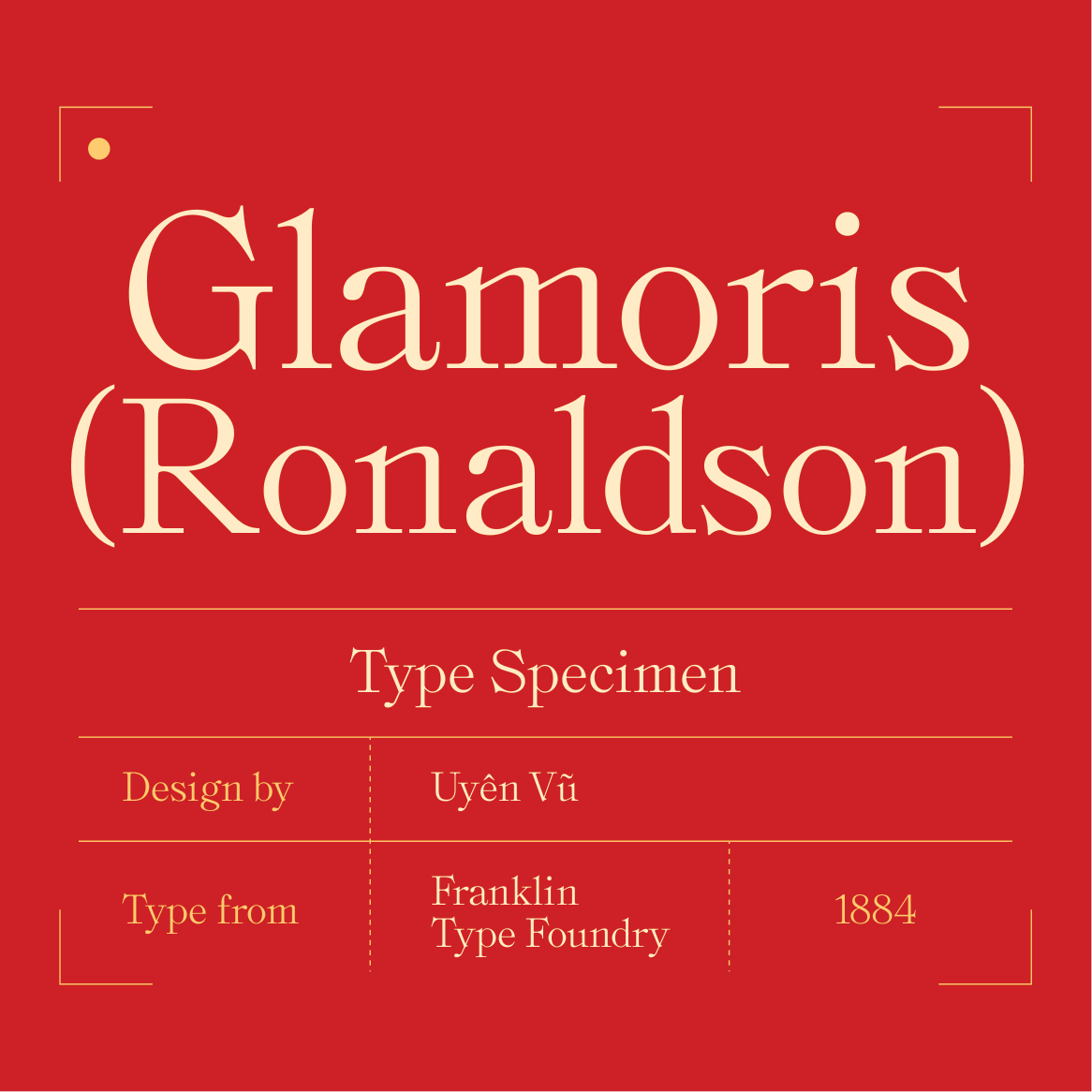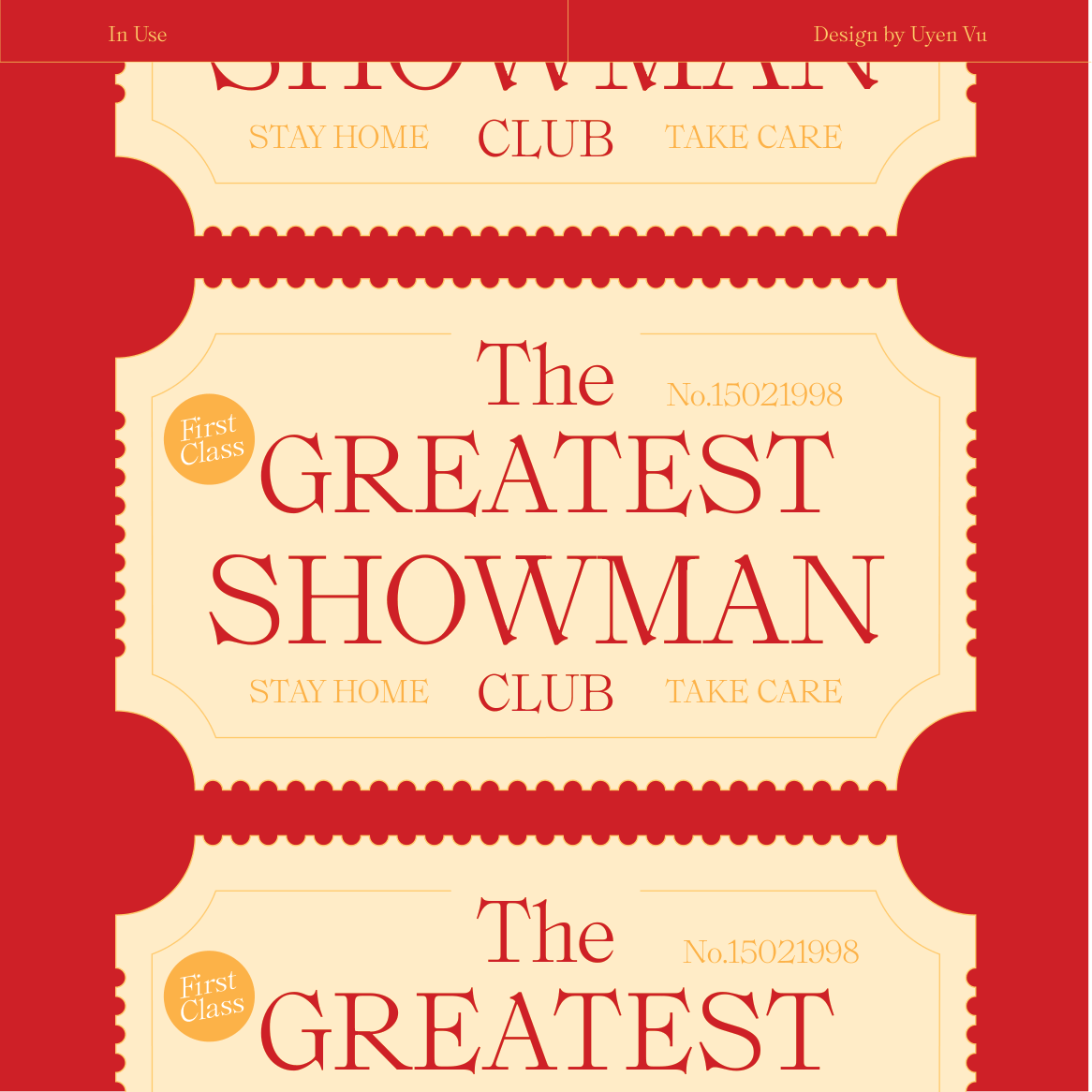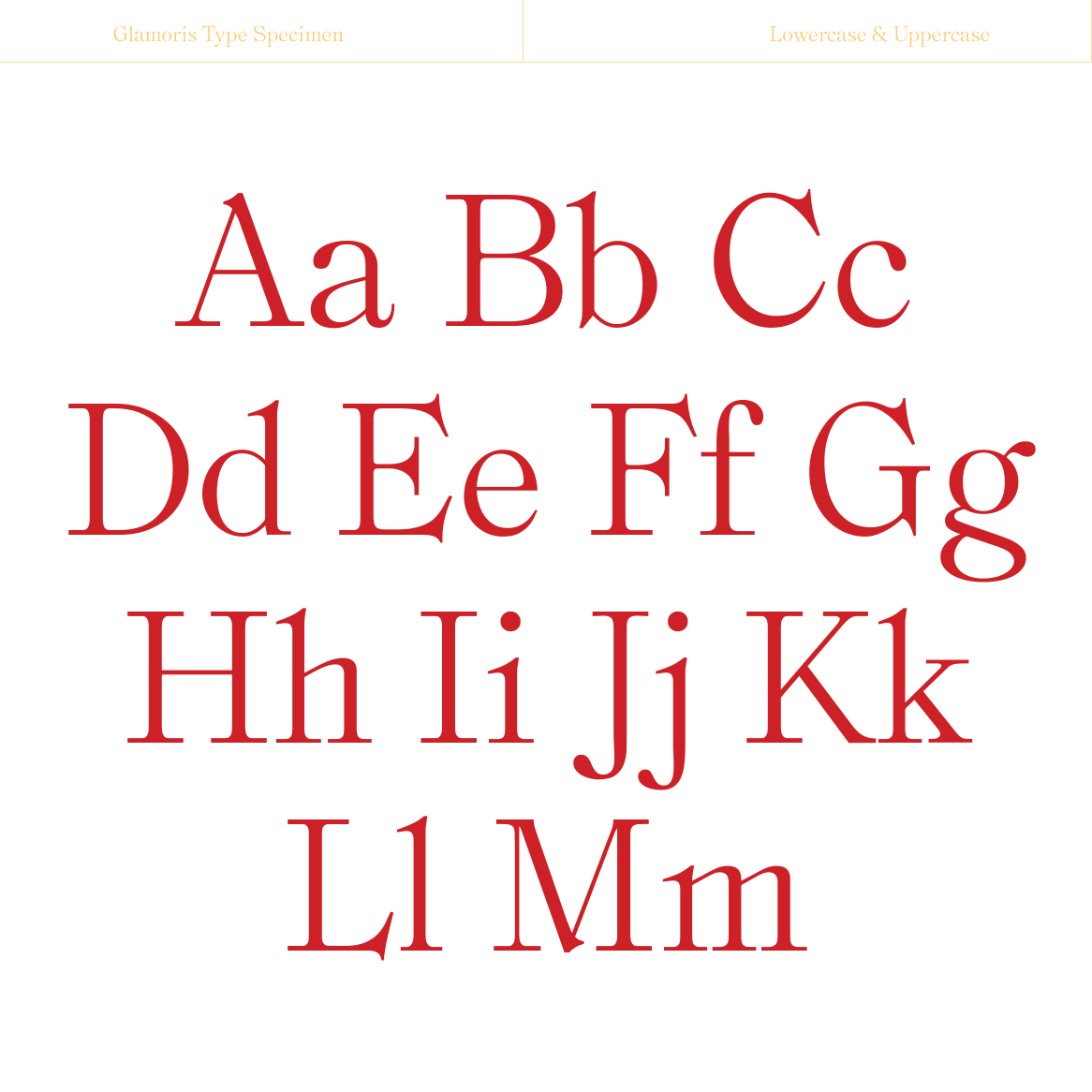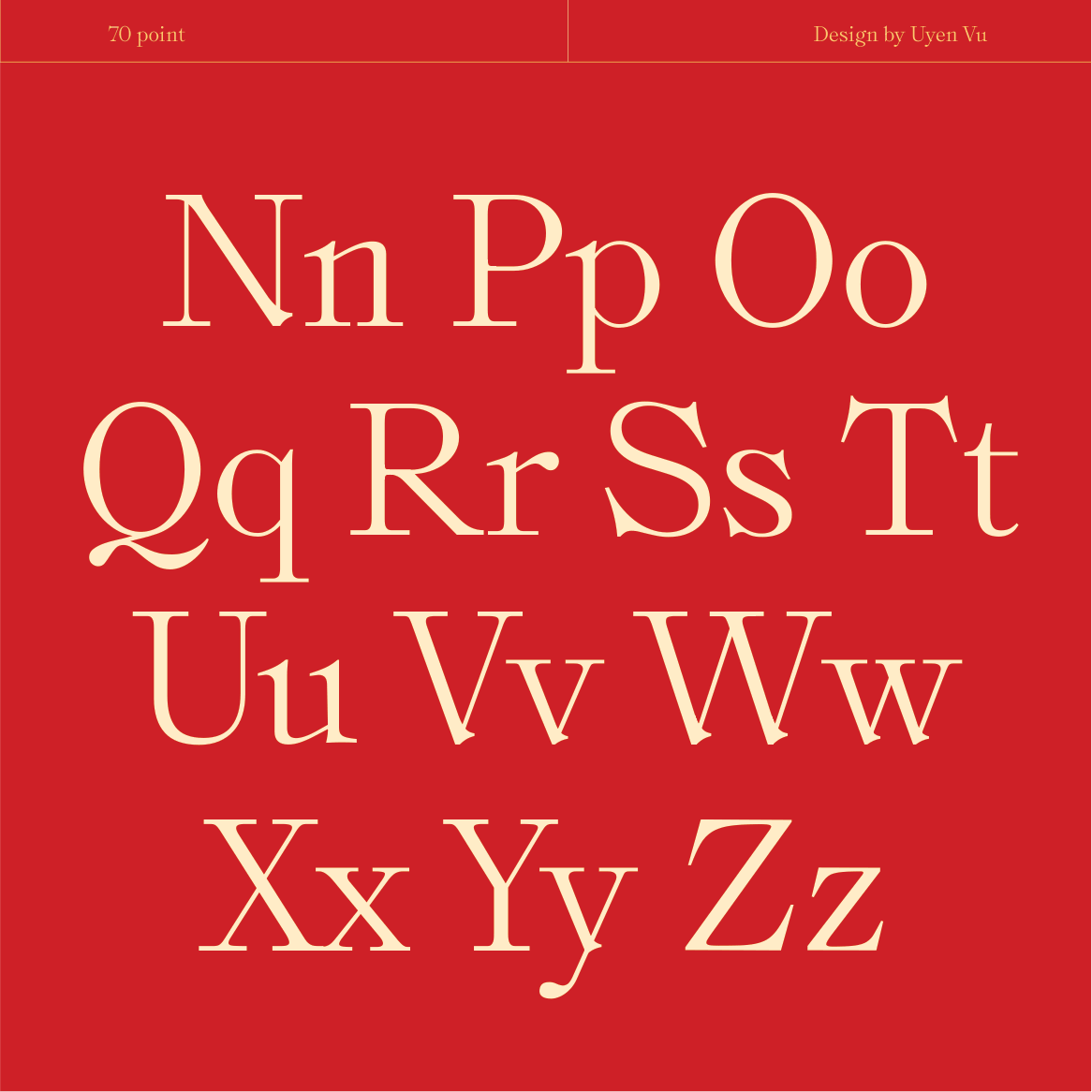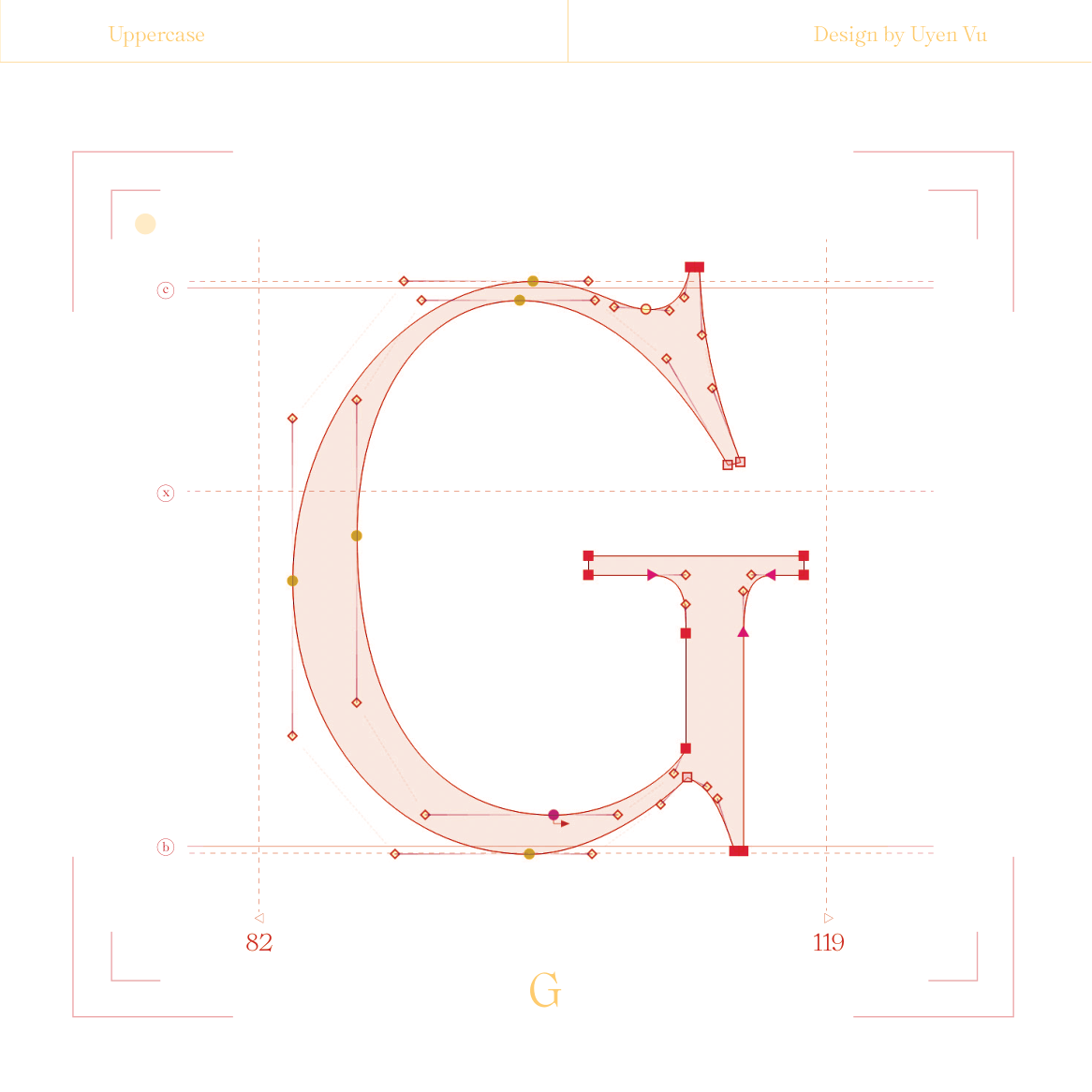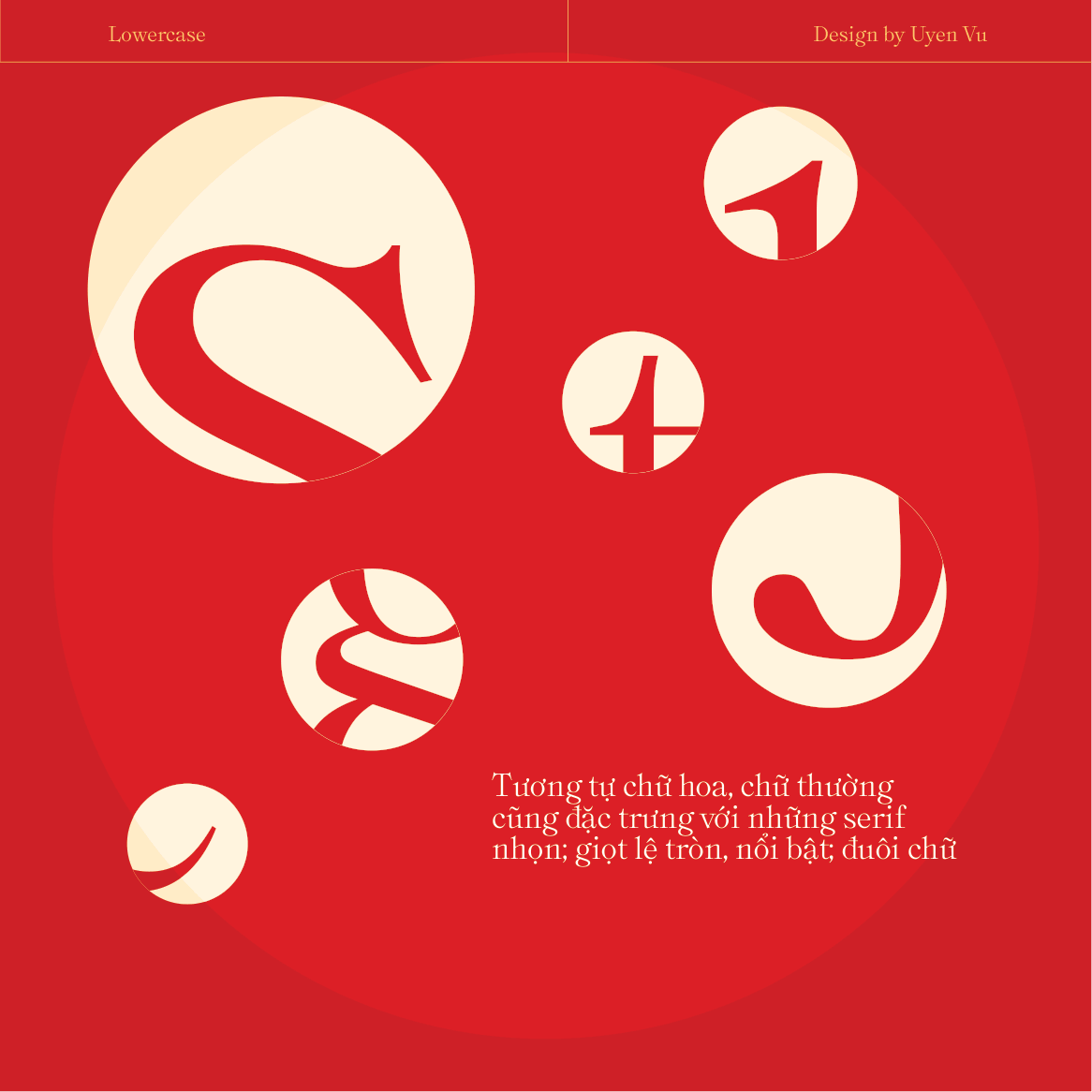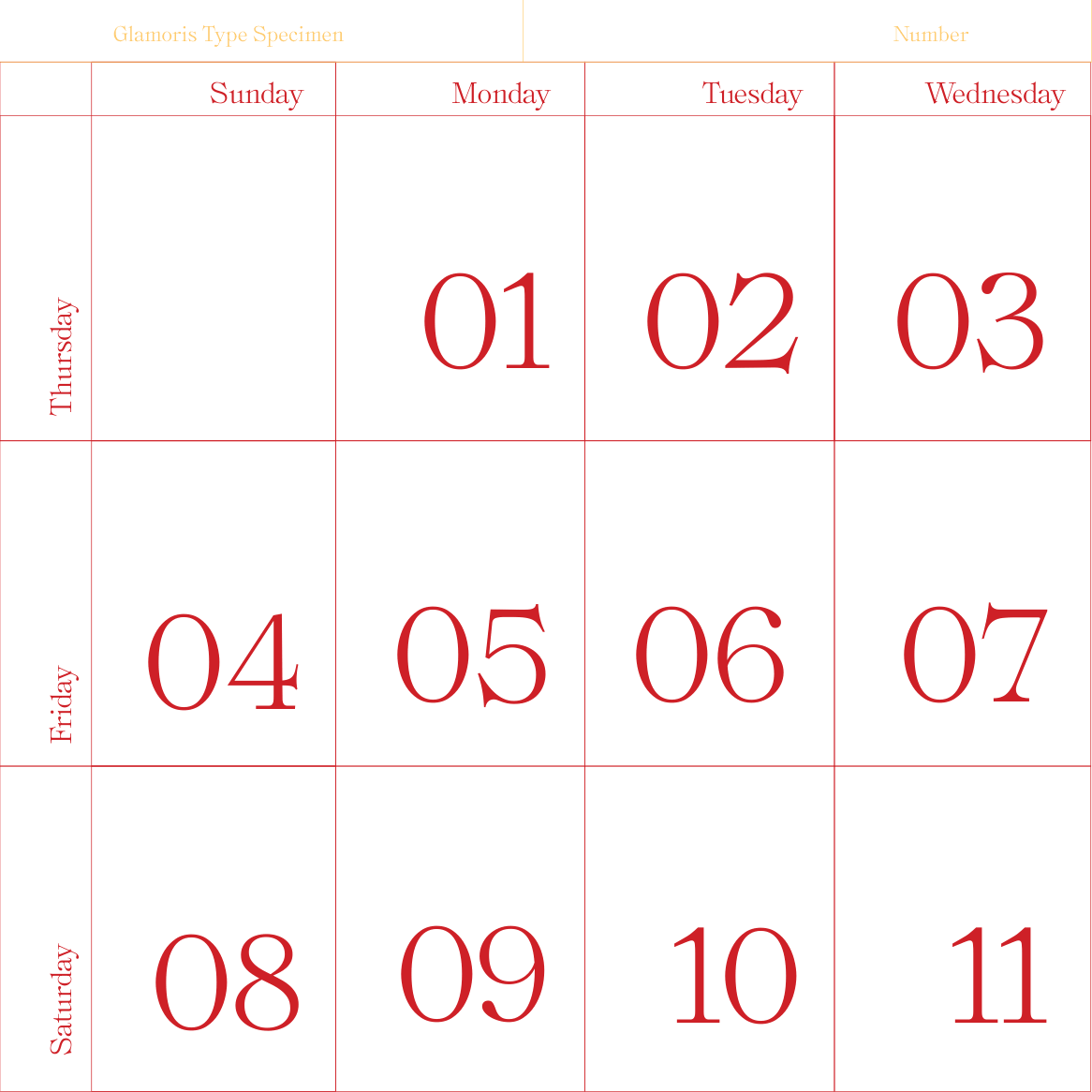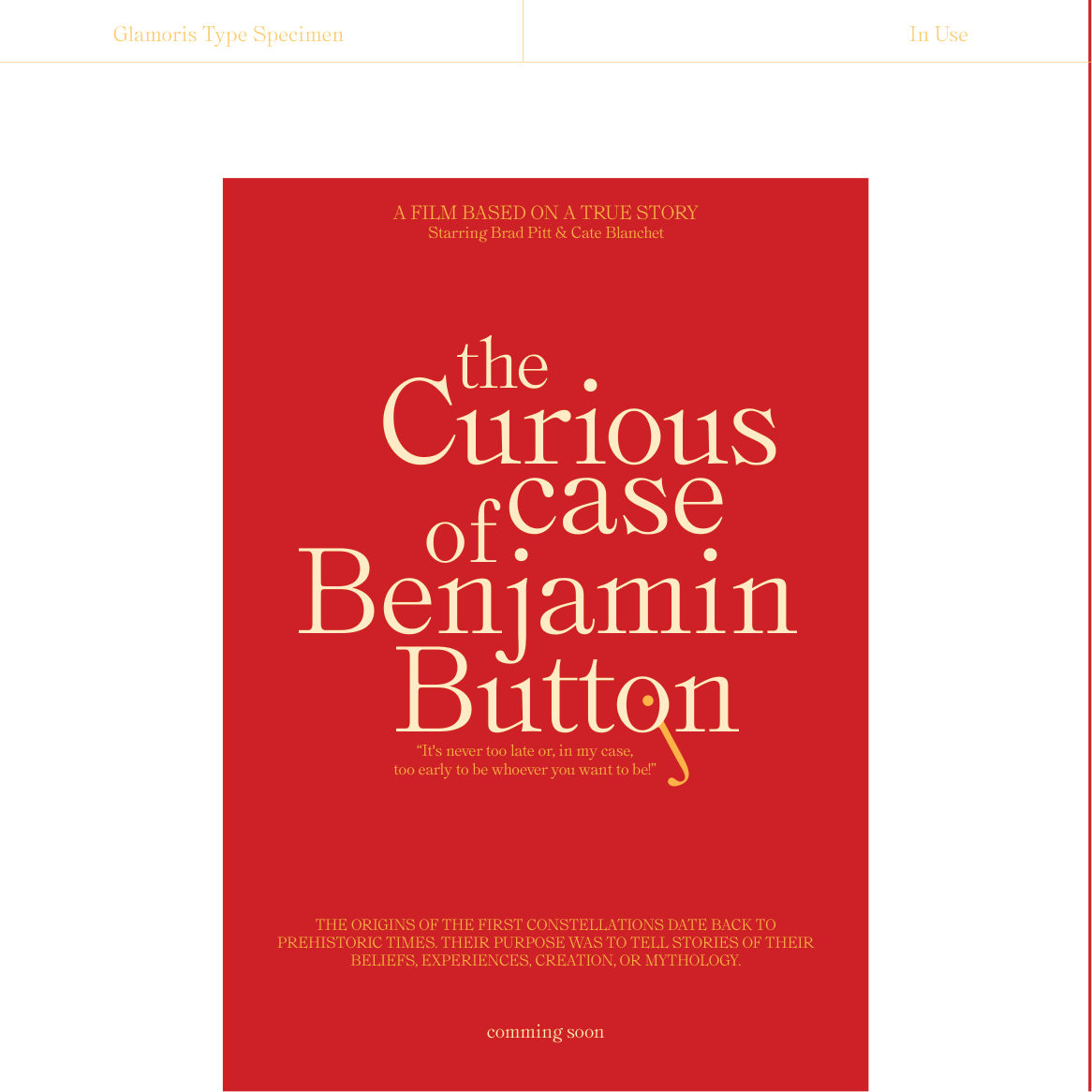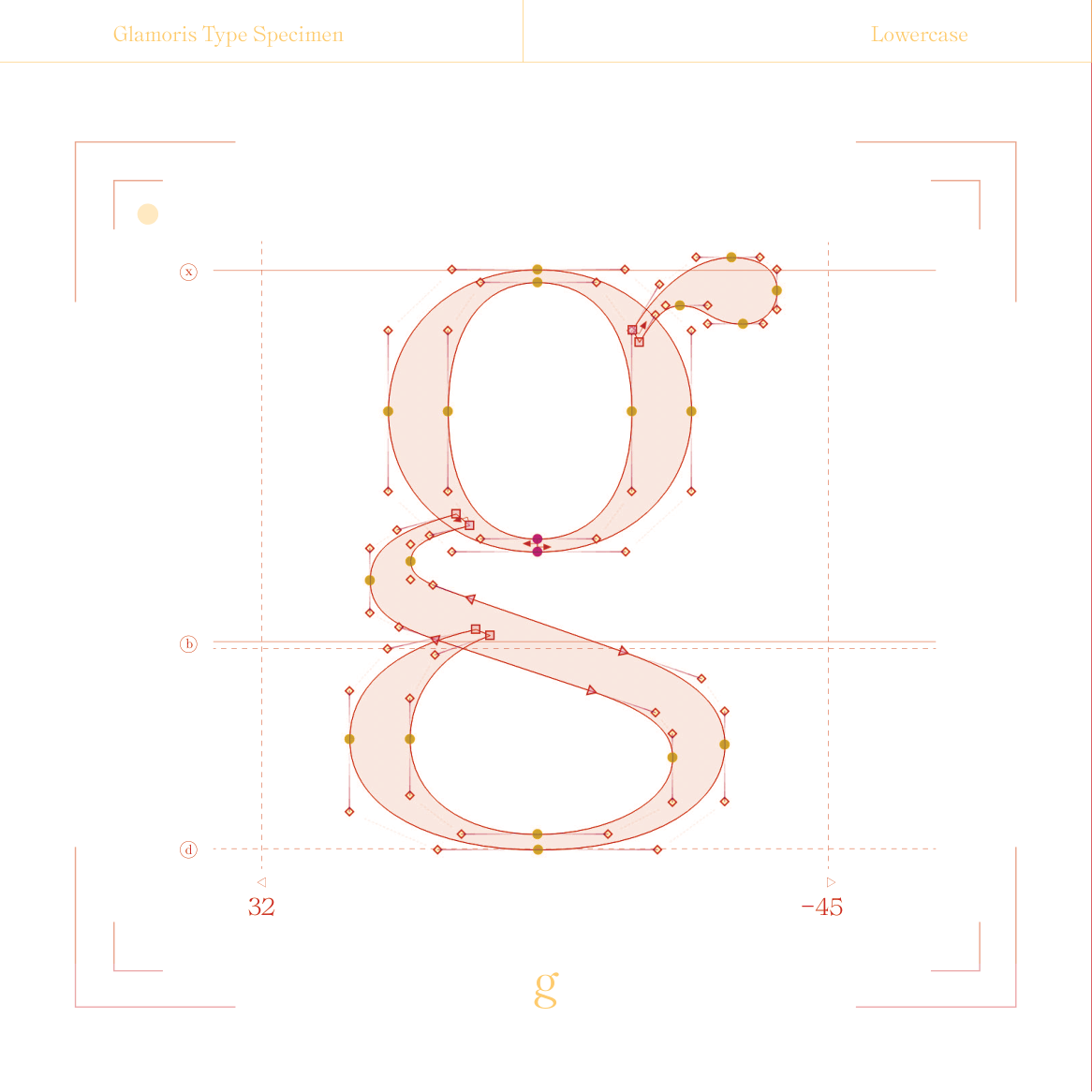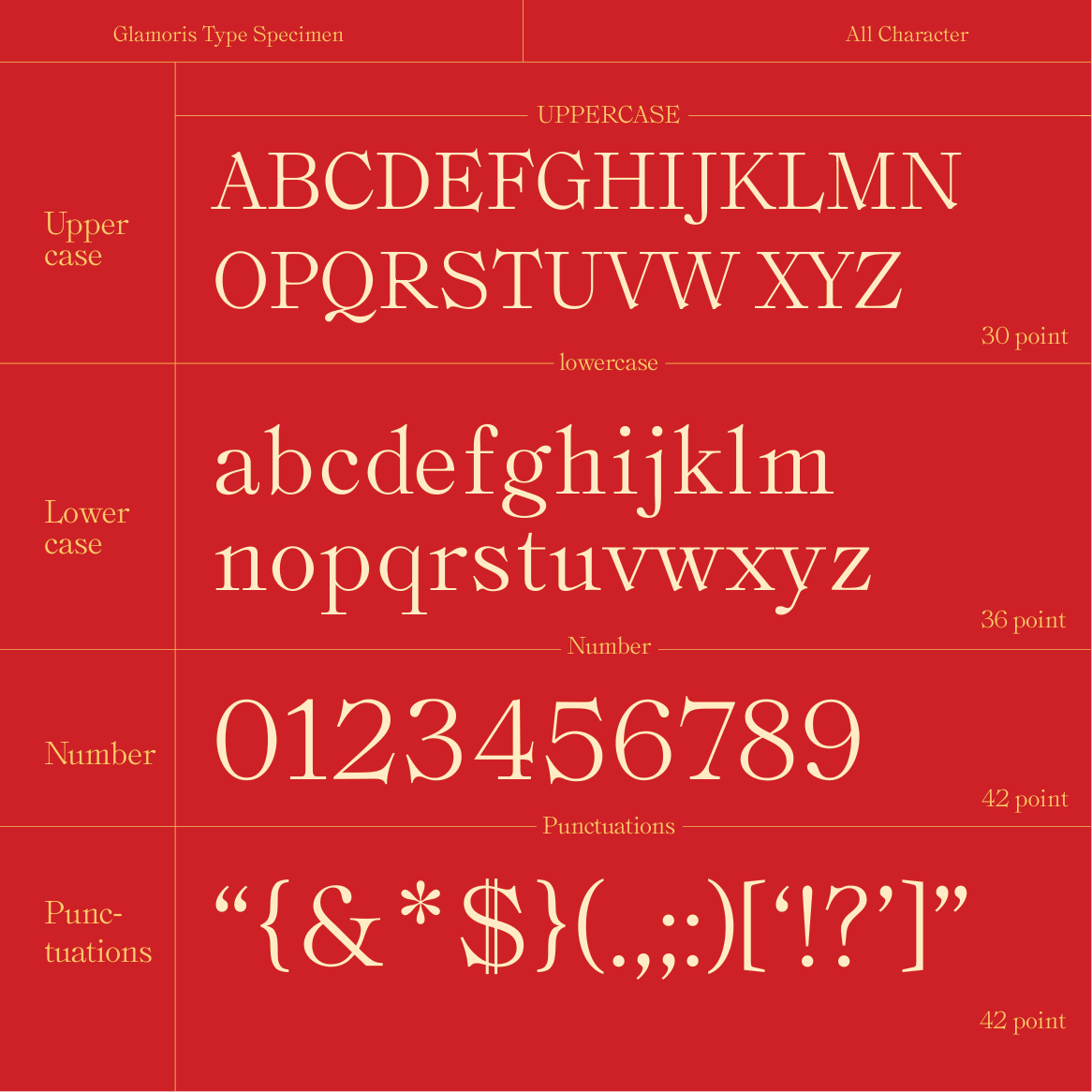
Glamoris
Về Glamoris: Lựa chọn bản Light từ bộ Ronaldson của Franklin Type Foundry, Glamoris phục dựng lại dáng chữ tròn bè cùng những nét serif dài kịch tính. Glamoris linh hoạt kết hợp giữa các nét vòm cứng cáp ở n hay m và độ tròn hơi thoi ở o hay c. Với từng ấy chi tiết, Glamoris hớp hồn ngay từ lần gặp đầu.
Transitional Serif
Display
Uyên Vũ
Glamoris
Romance
Glamoris
Theatrical
Glamoris
Melodrama
Glamoris
Pompous Ending
Glamoris
It is in the name that tells all needed to know about Glamoris. Theatrical, Dramatic, and Extravagant are some buzzwords to capture the essence of Glamoris.
Glamoris
Under the influence of Ronaldson by Franklin Type Foundry, Glamoris plays into the excessive spikey forms of its original design. Lighter stroke does not equate dimmer spotlight. Lighter stroke and wide proportions actually allow more to accentuate the edgy and elaborate serifs, giving even more drama to a master puppetshow. With greater interspace, Glamoris cements its place as the only main character all desire to be. All that brings Glamoris to shine best as a display type in projects that aims to stir much drama.